7 Situs Generator Font Twitter Terbaik | Unik, Lucu dan Aesthetic
Tech HackFont Twitter yang unik dan lucu mungkin pernah beberapa kali kamu temui digunakan sejumlah pengguna media sosial Twitter dalam cuitan mereka.
Bagaimana mereka melakukannya? Apakah mereka hack media sosial Twitter? Ternyata, tidak. Ada beberapa rahasia Unicode kecil yang memungkinkan membuat font tweet menjadi tebal, miring, atau lainnya.
Rahasianya cukup sederhana, Unicode mengubah sejumlah karakter menjadi lebih dari 100.000 jenis bentuk karakter yang unik, lucu, dan berbeda dari yang umumnya kamu temui.
Jadi karakter yang ada di keyboard kamu sebenarnya hanyalah sebagian kecil, dari kemungkinan karakter yang dapat ditampilkan oleh sebagian besar komputer dan perangkat.
Berikut ini Jaka sudah merangkum sejumlah situs dan aplikasi generator font Twitter yang bisa kamu coba. Cukup ketik, lalu copy-paste ke Twitter kamu.
1. Lingojam
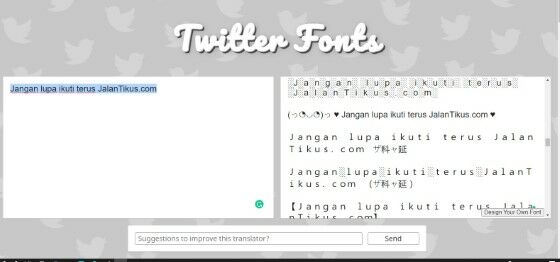
Lingojam merupakan salah satu situs generator font tweet yang menyediakan puluhan jenis font dan karakter unik yang bisa kamu gunakan di Twitter dan media sosial lainnya.
Kelebihan lainnya dari situs ini adalah kamu bisa mendesain sendiri font tweet yang hendak kamu cuitkan sehingga bisa menyesuikan keinginan dan kebutuhan kamu.
Tentunya menggunakan situs ini bisa bikin kamu lebih praktis dalam mengirimkan cuitan yang lucu ke teman-teman kamu.
2. YayText
Suka menggunakan font tweet yang simpel, tidak ribet, dan tetap unik ketika dibagikan melalui cuitan di akun media sosial Twitter kamu?
Kamu bisa coba situs generator YayText. Selain mudah untuk digunakan, kamu cukup ketik dan copy-paste saja, desain yang diberikan pun cukup simpel dan unik.
Kamu bisa mengetik dengan desain font yang sederhana dan tidak ribet, seperti menggunakan font dengen efek Short strikethrough, Long strikethrough, Short slash, dan sebagainya.
3. Messletters
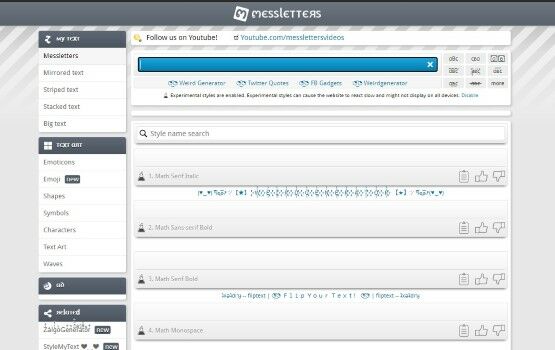
Apakah kamu mengenal nama-nama font seperti Math Serif Bold, Math Sans-serif Bold, atau Math Script (Royal) Bold?
Jenis-jenis font tadi bisa kamu temukan dan digunakan pada situs generator Messletters, tidak hanya huruf saja yang akan kamu temui.
Sejumlah emoticon dan emoji lucu turut bisa kamu temukan dan gunakan dari situs generator ini, sehingga cuitan kamu akan tampak lebih bervariasi.
4. Capitalize My Twitter
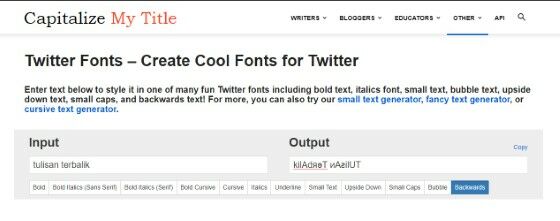
Pernah mencoba menulis dan mengirimkan cuitan di Twitter dengan tulisan yang terbalik dari tulisan pada umumnya?
Situs generator Capitalize My Twitter menyediakan sejumlah pilihan font yang bisa copy-paste untuk digunakan di Twitter maupun di media sosial lainnya, termasuk tulisan yang terbalik.
Kamu dapat menggunakan font tweet secara virtual ini di mana saja termasuk di profil Twitter, nama Twitter, tweet, dan pesan langsung (DM) kamu.
5. Twitter Font Fix
Berbeda dengan rekomendasi Jaka yang lainnya, cara mengubah font Twitter yang satu ini memanfaatkan ekstensi di browser laptop atau PC Google Chrome.
Ekstensi ini bernama Twitter Font Fix, tetapi fungsinya hanya untuk mengubah ukuran font cuitan yang ditampilkan agar tidak terlalu kecil atau terlalu besar.
6. FontVilla
Sama seperti generator font tweet lainnya, FontVilla menyediakan ratusan beragam jenis gaya dan desain font unik yang bisa kamu coba.
Font lucu untuk Twitter ini tidak hanya membantu menarik perhatian pengikut kamu tetapi juga membantu meningkatkan jangkauan cuitan dan meningkatkan jumlah orang yang mengikuti profil kamu.
Font ini dapat membantu dan secara positif berkontribusi pada keberadaan Twitter kamu, membuat kamu tampak unik dan berbeda dari akun lainnya.
7. Fonts For Twitter
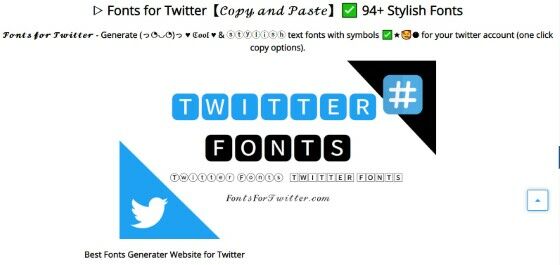
Teks apa pun yang dihasilkan dari situs Fonts For Twitter dapat dengan mudah berfungsi di Instagram dan Facebook, meski terkadang Facebook ada masalah dengan beberapa teks. Namun, sebagian besar berfungsi dengan baik.
Generator ini juga berfungsi pada pesan teks di WhatsApp. Terutama jika kamu menggunakan iPhone maka 100 persen semua jenis teks yang dihasilkan akan mendukung perangkat ini.
Namun, jika kamu ingin mengirim kepada seseorang yang menggunakan HP Android mungkin hanya 80 persen yang dapat berfungsi dengan baik.